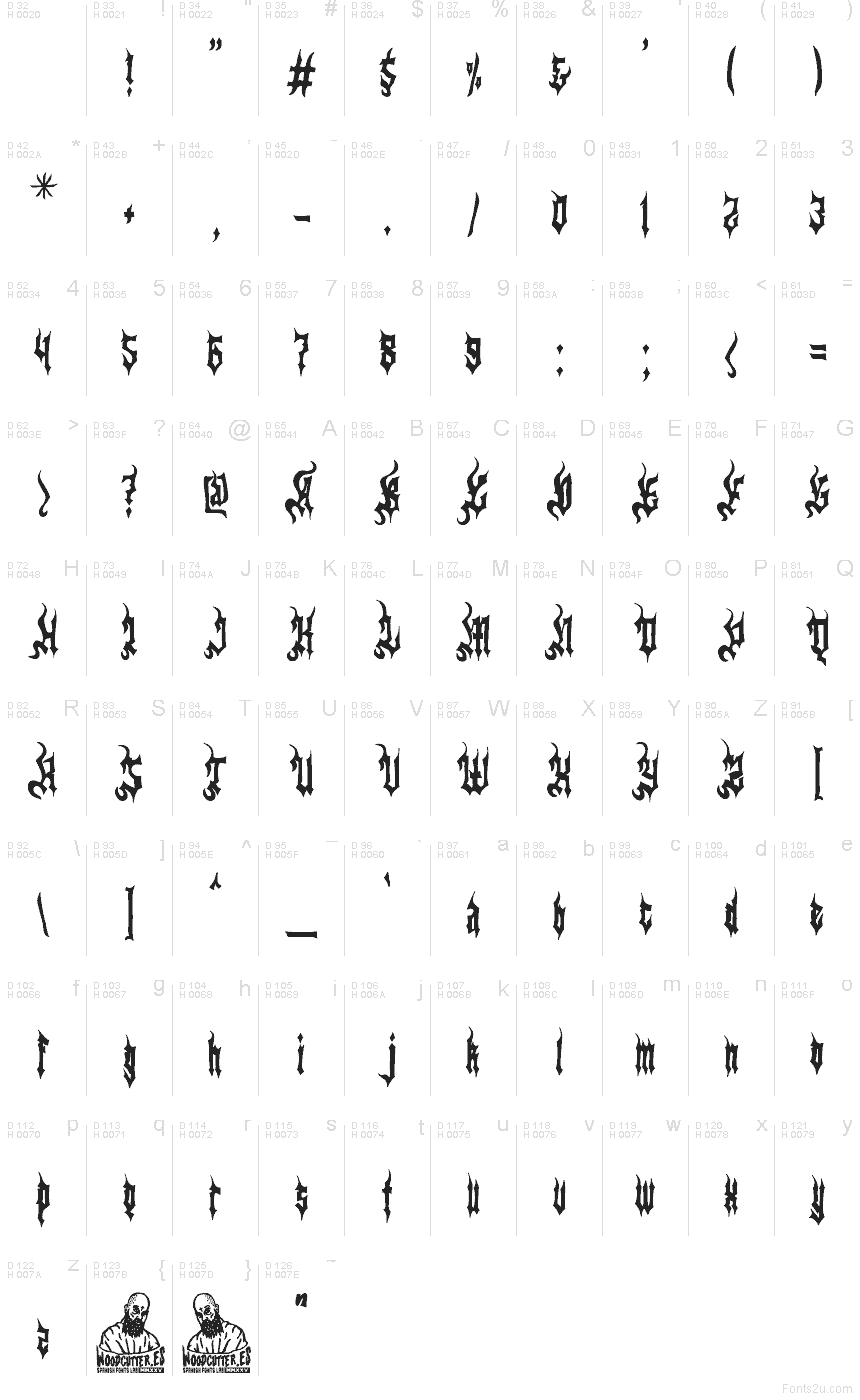
Danger Squad
Danger Squad od Woodcutter Manero je bezplatné gotické písmo s ostrými tvarmi a výbežkami podobnými plameňom na hlavných ťahoch. Písmená majú zlámané hrany a úzke vnútro, čo dizajnu dodáva tvrdý, uhlovaný rytmus – pocitovo bližší k tetovaniu než ku klasickému pätkovému písmu.
Danger Squad skvele funguje na plagátoch metalových kapiel, hororových tituloch, logách hier, streetwearovej grafike, letákoch na podujatia či na výrazných obaloch, pretože jeho zubatý charakter prináša silný vizuálny akcent bez potreby ďalších dekorácií. Toto bezplatné písmo sa hodí aj na citáty na plagátoch, obaly albumov a drsné nadpisy vždy, keď potrebujete dosiahnuť vyrytý, agresívny vzhľad.